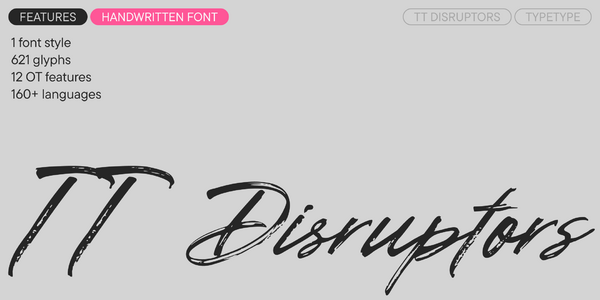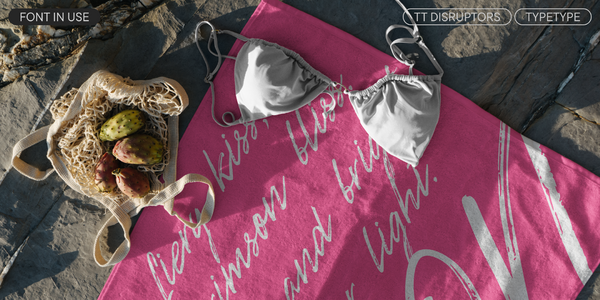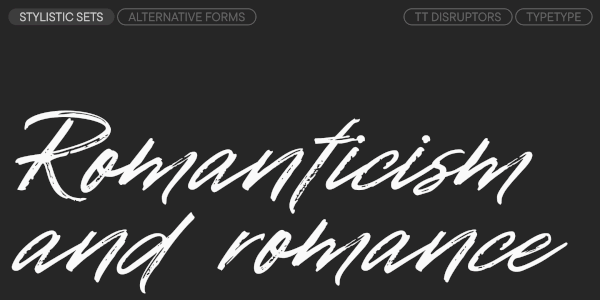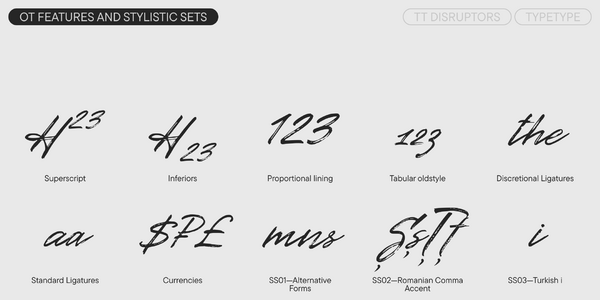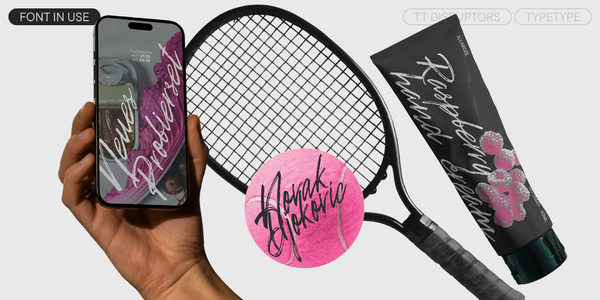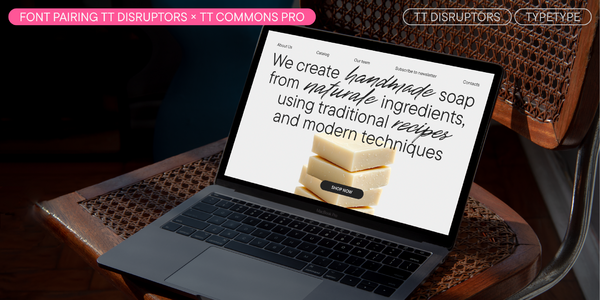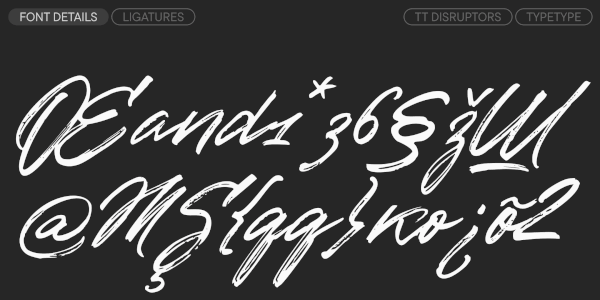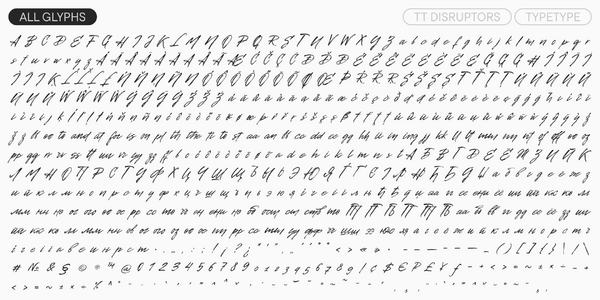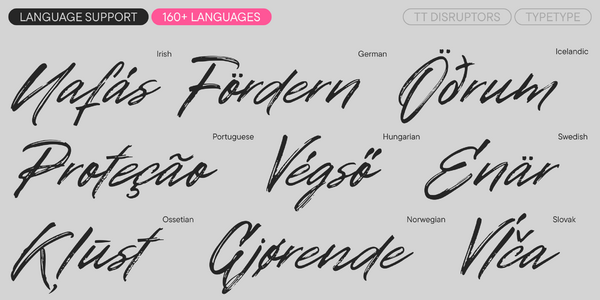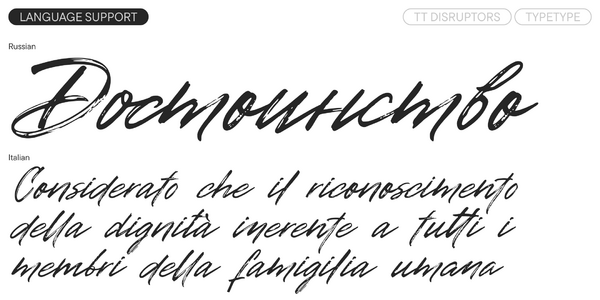
TT Disruptors
TT Disruptors — ТТ Дизрапторс
Произносится «ТТ Дизрапторс». «Disruptors» — производное слово от disrupt, в переводе с английского «разрушать». Буквы «TT» являются аббревиатурой названия компании.
TT Disruptors — дуктальный рукописный шрифт, созданный с помощью маркера. Его характер своенравный и эмоциональный, но при этом тёплый и душевный.
О гарнитуре TT Disruptors
Встречайте новый декоративный TT Disruptors!
Это самобытный скрипт с уникальным живым характером.
TT Disruptors — дуктальный рукописный шрифт, созданный с помощью маркера. Его рисунок уникален: потёртости, неравномерная толщина штрихов и удлинённые выносные элементы придают ему живую, динамичную текстуру и ощущение рукотворности. Характер этого шрифта своенравный и эмоциональный, но при этом тёплый и душевный.
TT Disruptors богат контекстными альтернативами, которые позволяют сделать его более выразительным. Для часто встречающихся букв мы разработали альтернативные варианты форм. При наборе они меняются автоматически в зависимости от того, какие символы оказываются по соседству, чтобы текст выглядел максимально интересно при любых буквенных комбинациях.
Кроме того, TT Disruptors включает функциональные лигатуры для наиболее часто встречающихся двух- и трёхбуквенных сочетаний, что добавляет тексту разнообразия, ломает монотонность набора и вносит элемент неожиданности. Для достижения максимального эффекта мы рекомендуем всегда использовать функции контекстных альтернатив (calt) и стандартных лигатур (liga).
Этот шрифт отлично подойдёт для оформления упаковки, брендинга и создания айдентики. Он станет идеальным выбором для проектов, где важны рукотворность, индивидуальность и экспрессия.
В TT Disruptors входит:
• 1 начертание;
• 621 знак;
• 12 OpenType фич;
• Поддержка 160+ языков.
TT Disruptors — рукотворный, динамичный, вдохновляющий!
Антонина Жулькова
onum | Oldstyle Figures
1 2 3
SS01 | Alternative Forms
s t а в
SS02 | Romanian Comma Accent
Şş Ţţ
SS03 | Turkish i
i
liga | Standard Ligatures
an bb ГП
dlig | Discretionary Ligatures
and ств